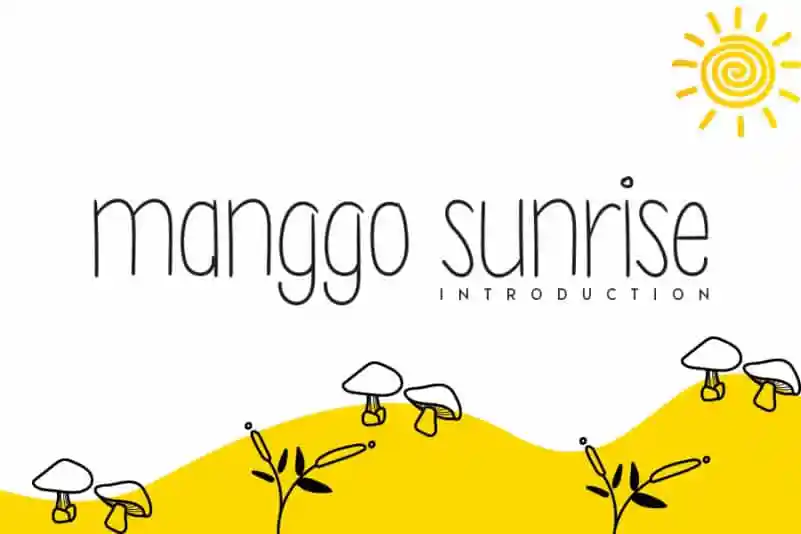
Manggo Sunrise Handwritten Font – Download Grátis
A Manggo Sunrise Handwritten Font é uma elegante fonte cursiva que carrega consigo uma graça quixotesca. Suas letras delicadas e esbeltas criam um olhar encantador, adequando-se a diversos estilos de design. Seja para gráficos pessoais ou profissionais, essa fonte é perfeita para adicionar um toque único e sofisticado a qualquer projeto. Sua elegância em tons suaves torna-a ideal tanto para aplicativos digitais quanto impressões físicas, criando texturas sutis que agradarão designers apaixonados por detalhes. Seja você designer de sites, gráficos ou editor de fotos, a Manggo Sunrise Handwritten Font é um recurso adicional inestimável para o seu arsenal de ferramentas digitais.